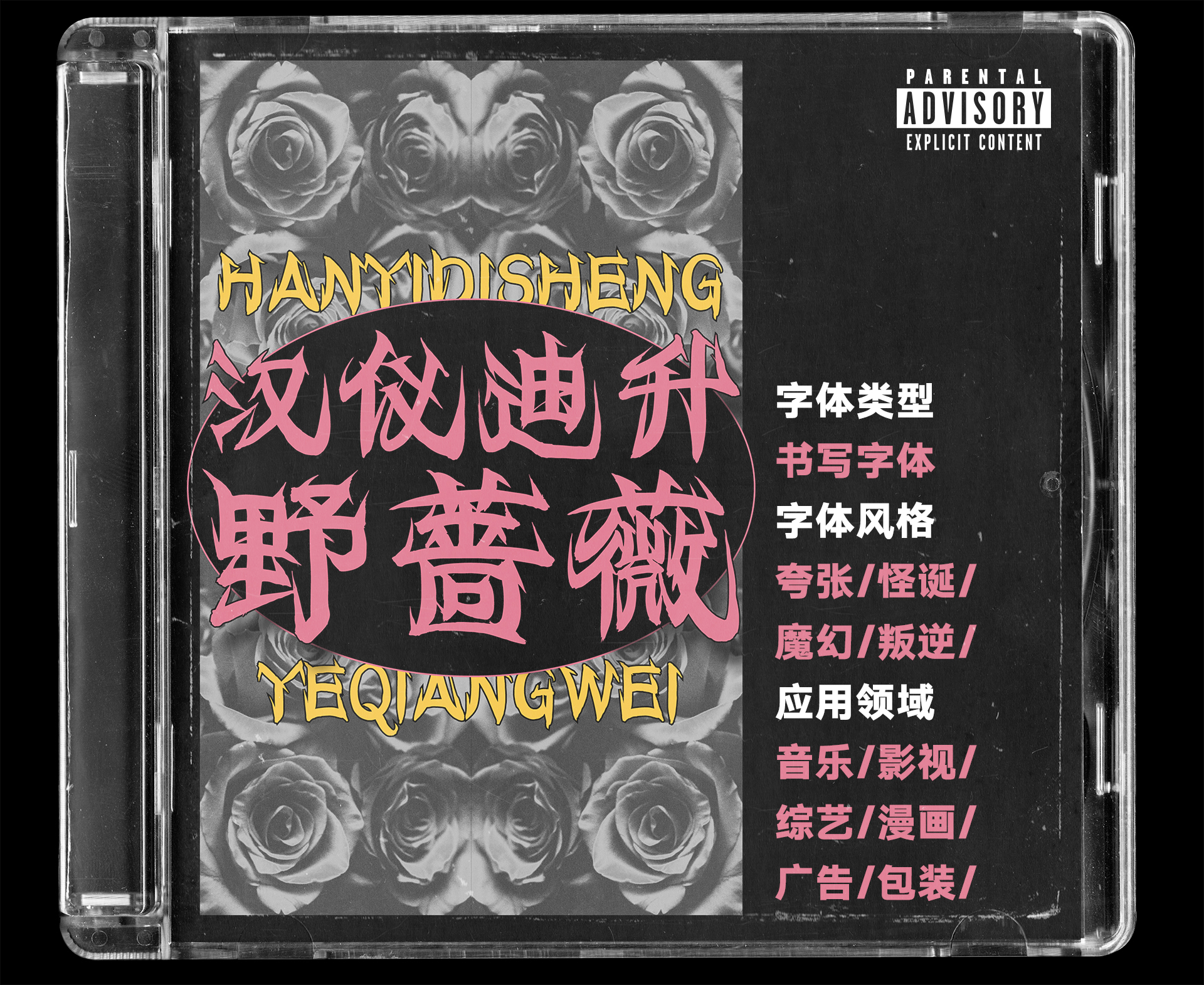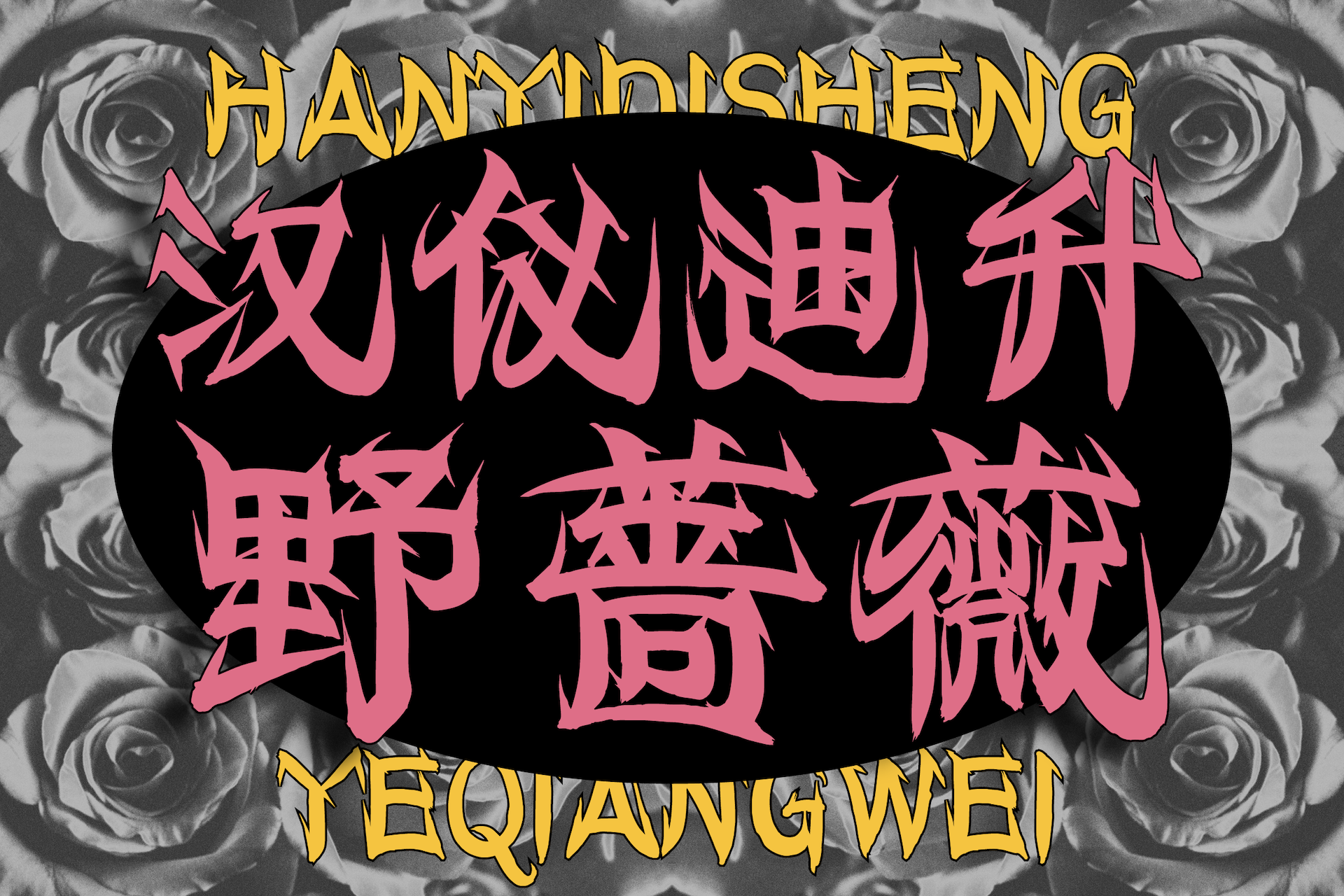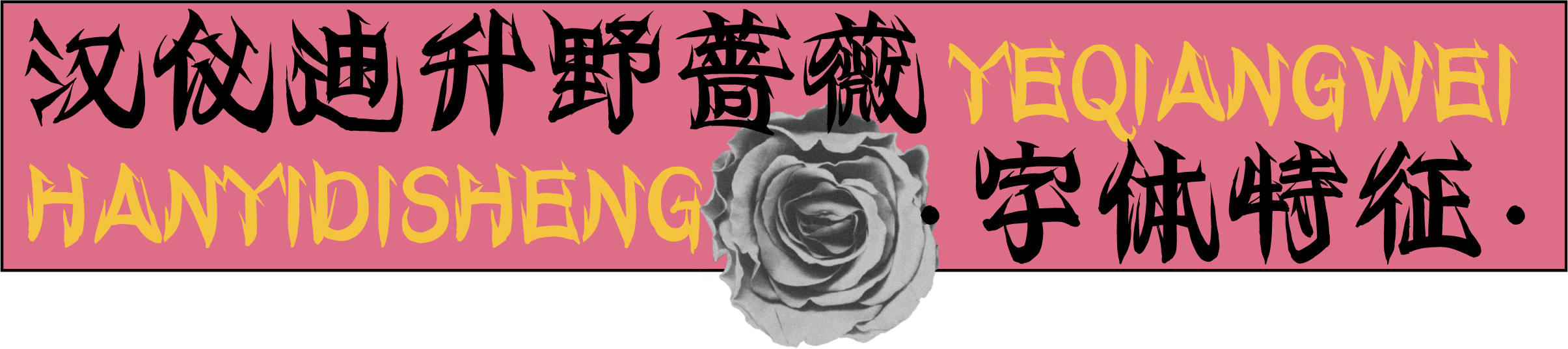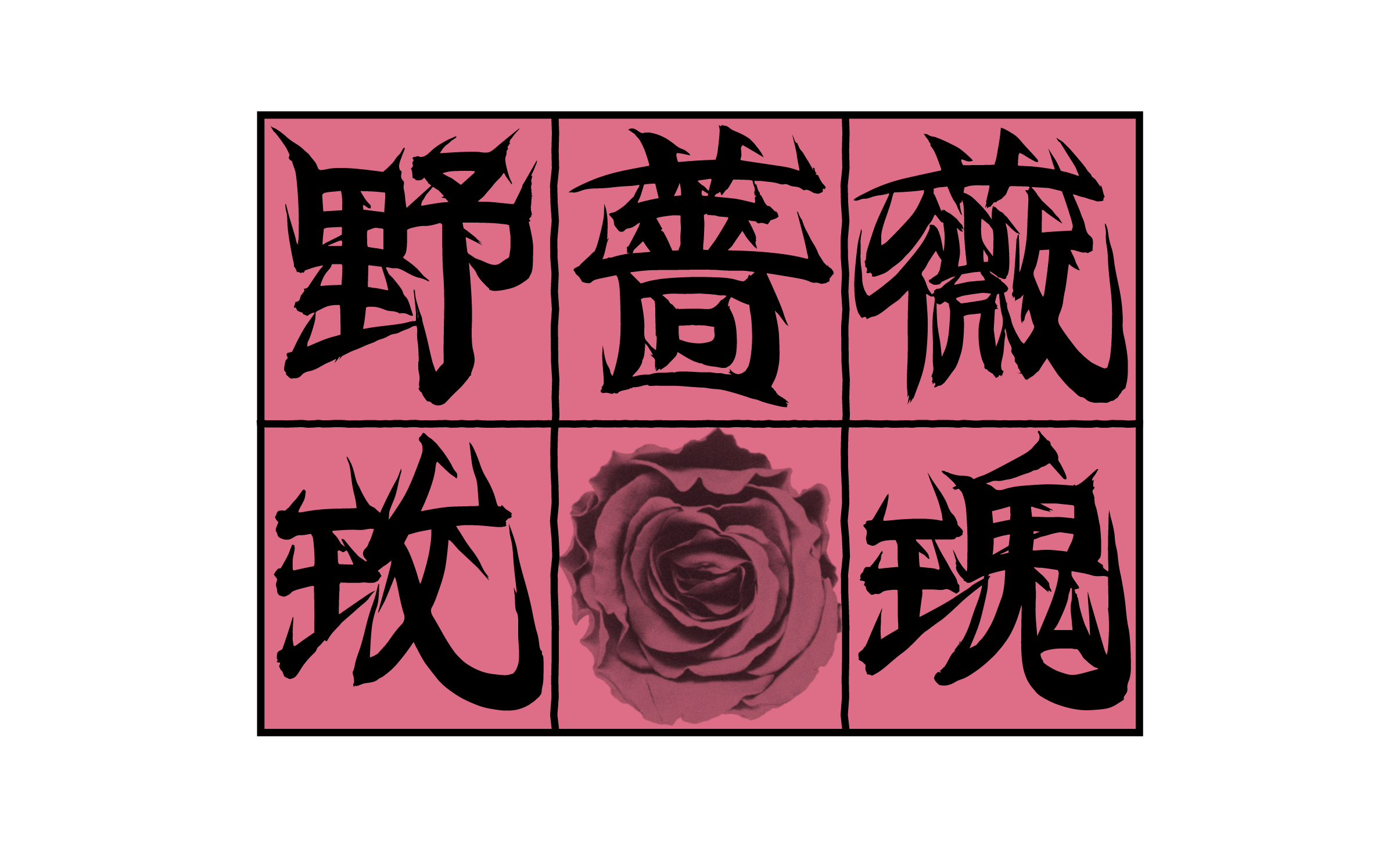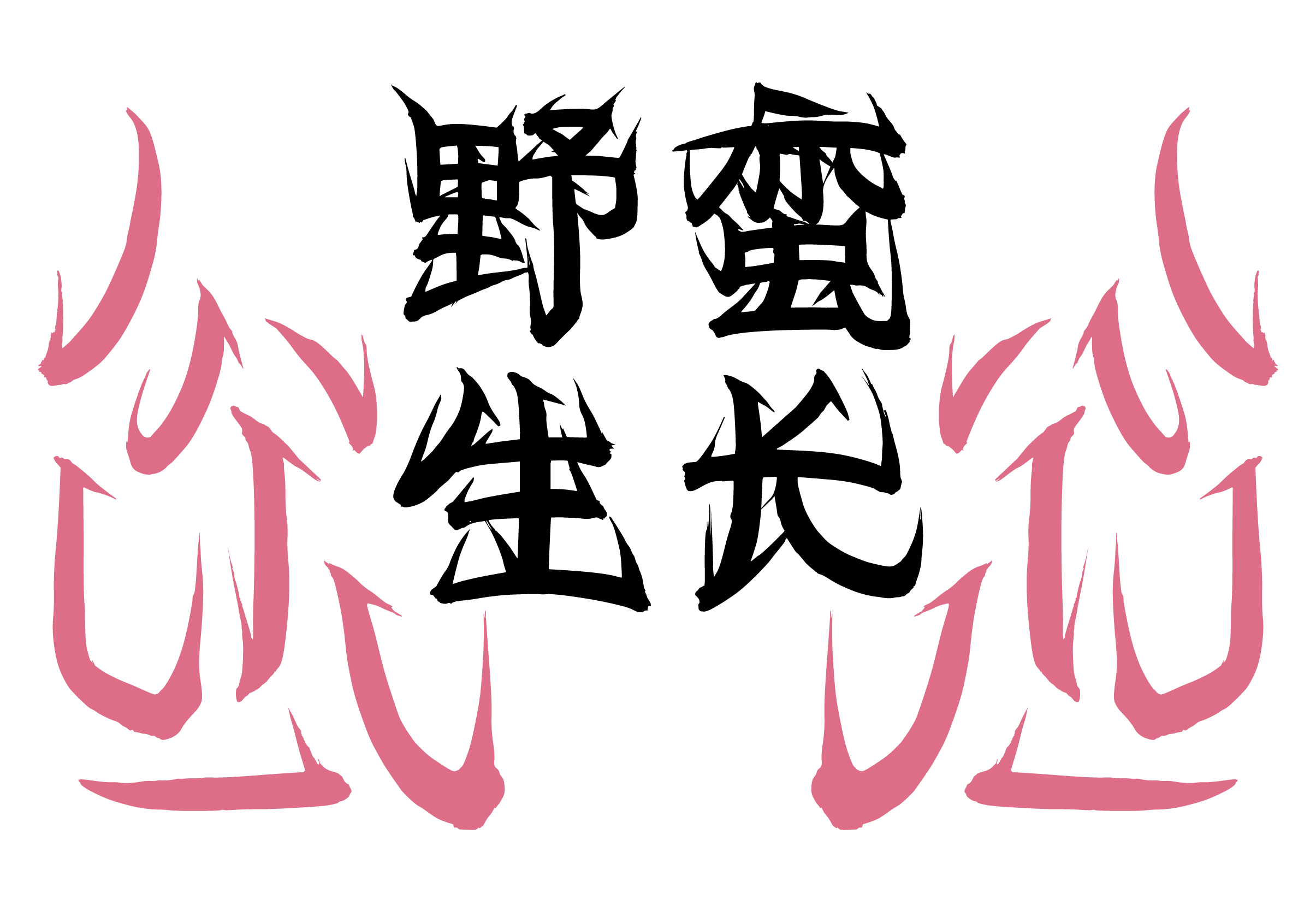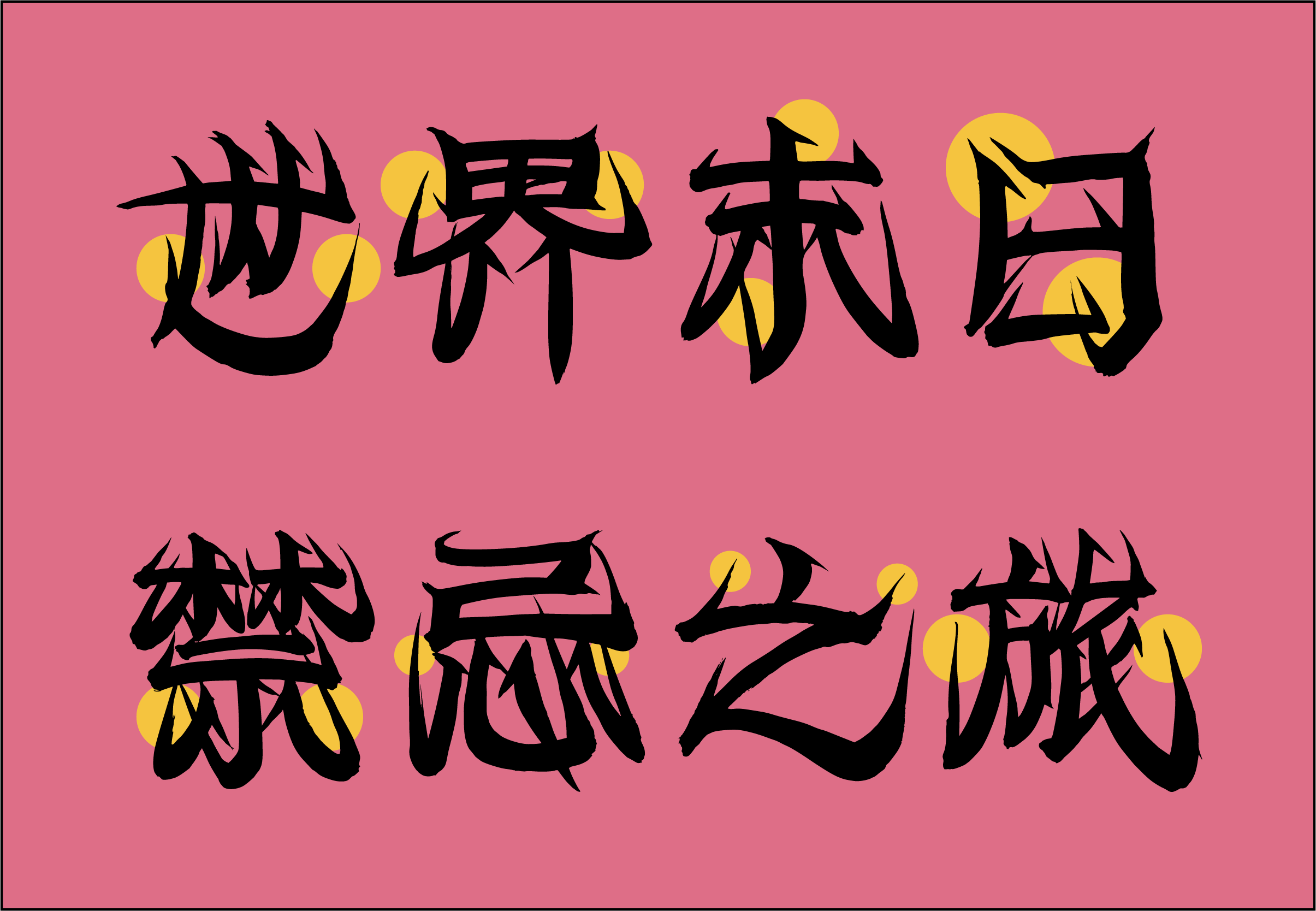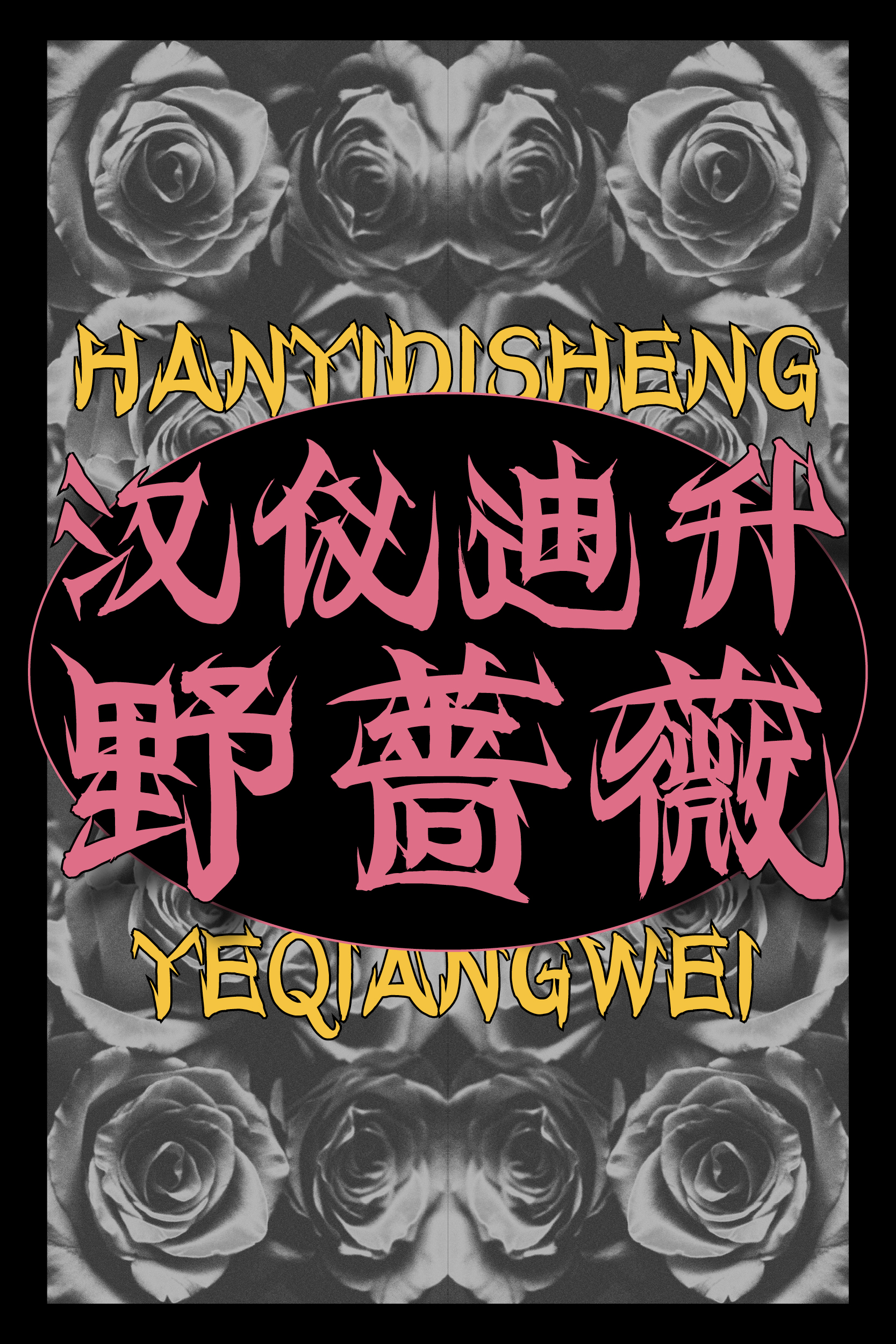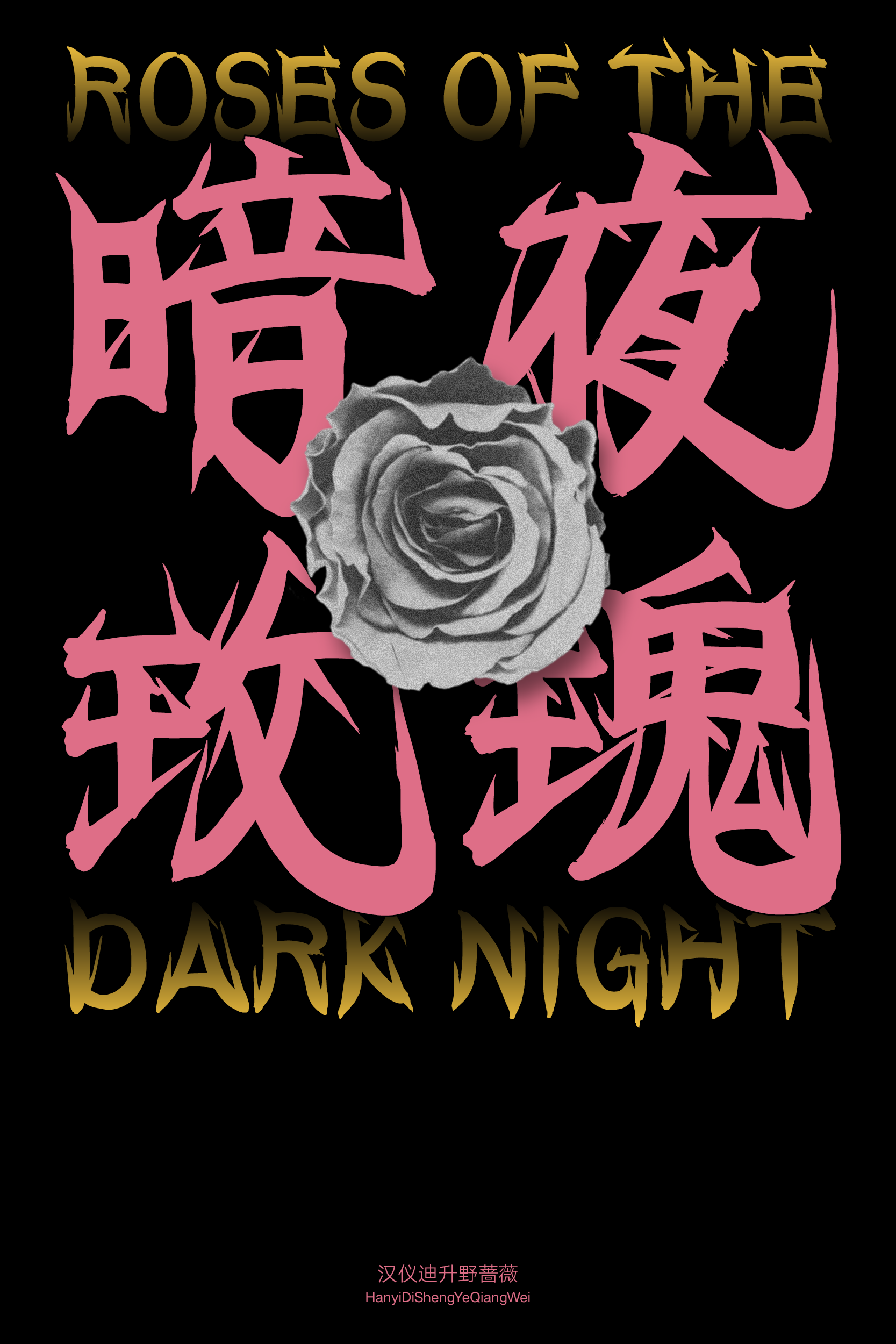
把野蛮生长的蔷薇做成字体
汉仪迪升野蔷薇,由汉仪字库签约作者迪升创作的这款手书情绪饱满,如野蔷薇肆意生长,绽放出野蛮的生命力。坚硬有力的笔画线条生出尖刺,表达着张扬、叛逆、不羁的个性,适合作为标题字体或少量文本装饰排版,应用于音乐节等活动、影视综艺、游戏动画等使用场景。
字形张扬,叛逆不羁。
有力的线条绽放出野蛮的生命力。
笔画起收生出尖刺,如荆棘丛生。